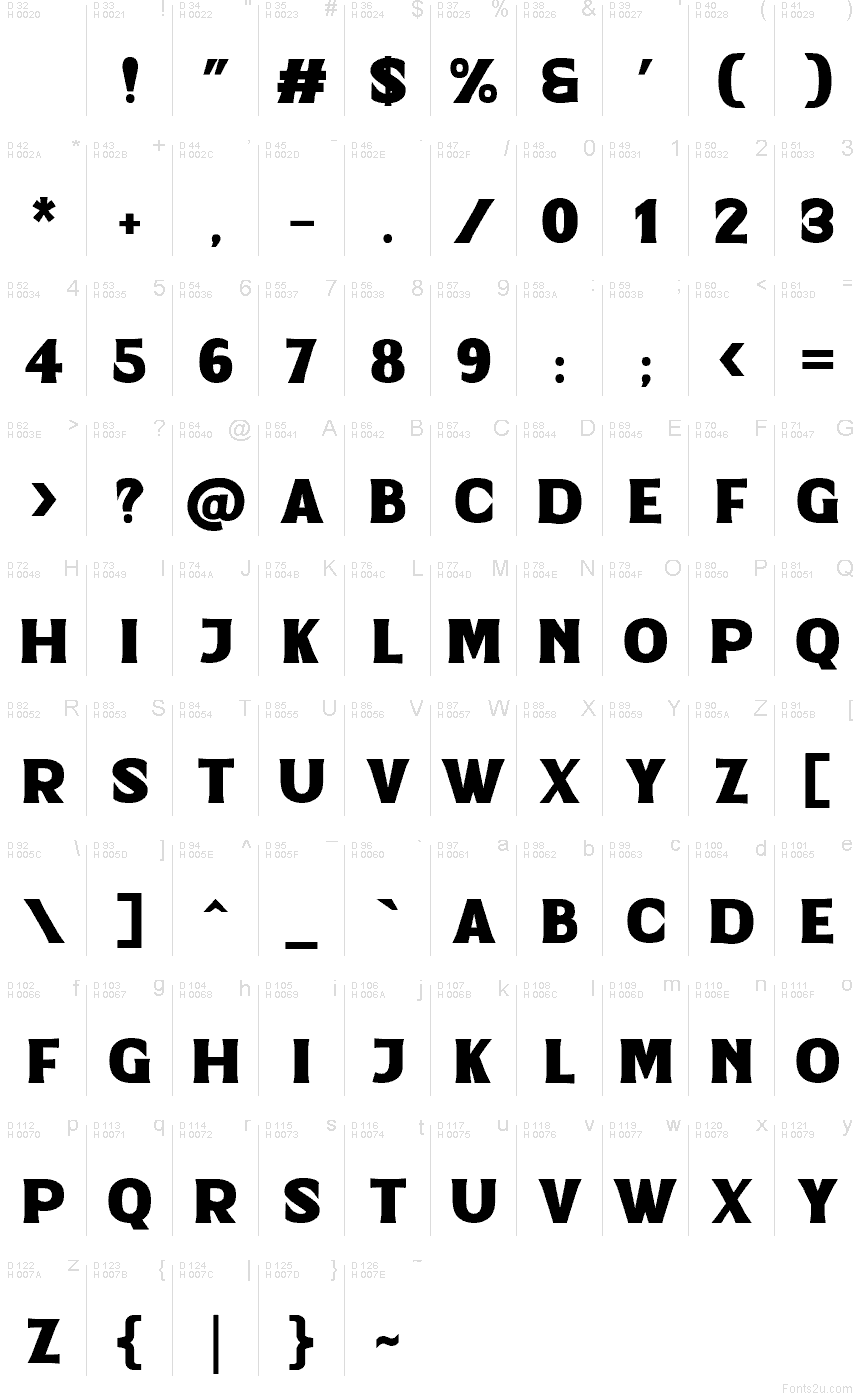
Goldener Bold, creata da Muhamad Fikry Nuralif di Fikryal Studio e parte della famiglia Goldener, è un font serif gratuito dal peso denso e profondo, caratterizzato da incisioni nette che rendono ogni lettera simile a un pezzo scolpito nel blocco. La sua base ampia e il ritmo serrato e sicuro la rendono di grande impatto senza risultare disordinata, anche quando utilizzata tutta in maiuscolo.
Con Goldener Bold otterrai risultati eccellenti su titoli di poster, copertine di album o libri, branding sportivo, packaging artigianali o per caffè, volantini di eventi, testate editoriali e testi d'impatto per siti web. Abbina questo font gratuito a un sans serif umanista pulito per il testo principale e applica una leggera spaziatura aggiuntiva alle dimensioni maggiori per far respirare i suoi dettagli incisi.